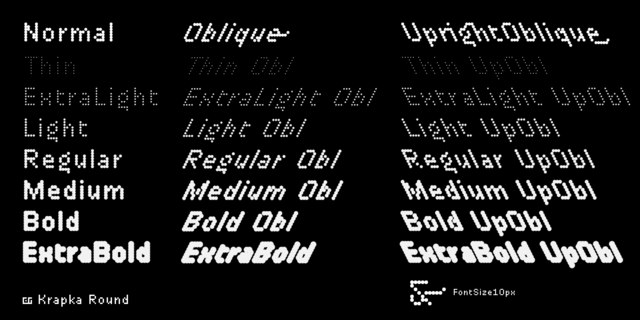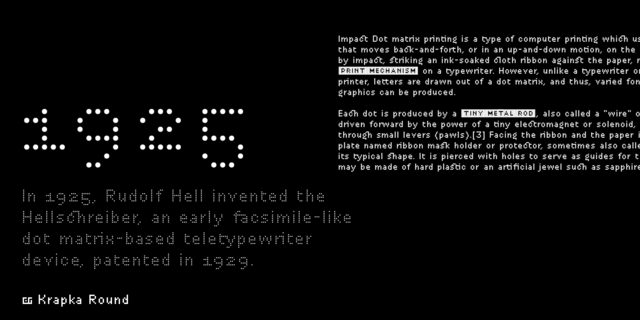
В этом шрифтовом семействе пиксель имеет круглую форму. Шрифт поддерживает функции OpenType и содержит капитель, лигатуры, минускульные цифры, дроби и индексы, исторические формы, стилистические наборы и росчерки. Также присутствуют символы, стрелки, и даже эмодзи. Для небольших текстов рекомендуется использовать DR Krapka Round FontSize10px с размером шрифта ровно 10 пикселей. Семейство шрифтов DR Krapka Round поддерживает европейские языки на основе латиницы, кириллицу, в том числе азиатскую, и греческий алфавит. Если вы хотите использовать шрифты с другой формой пикселей, есть и другие семейства DR Krapka: DR Krapka Square (квадраты), DR Krapka Rhombus (ромбы). Шрифт разработал Дмитрий Растворцев в 2020 году.
автоматический, компьютерный, машинный, матричный, инженерный, точный, заметный, броский, внушительный, уверенный, тяжелый, странный, экспериментальный, игривый, тесный, черный, мощный, прямоугольный, квадратный, стремительный, смелый, быстрый, решительный, срочный, рабочий, электронный, ровный, логичный, холодный, техногенный, твердый, устойчивый, городской, урбанистический, индустриальный, мужественный, армейский, промышленный, угловатый, активный, суровый, брутальный, игровой, мягкий, гладкий, пластмассовый, урбанистичный, психоделический
электроника, автоматика, компьютер, игра, фантастика, технологии, кирпич, игрушка, мультфильм, детская книжка, анимация, экскаватор, инженер, урбанистика, машина, инструмент, промышленность, армия, завод, станок, тара, склад, ремонт, депо, каска, униформа, вагон, автомат, шутер, экшен, страйкбол, стройка, стройматериалы, боевик, сталевар, рабочий, кубики, компьютерная игра Стилистика: